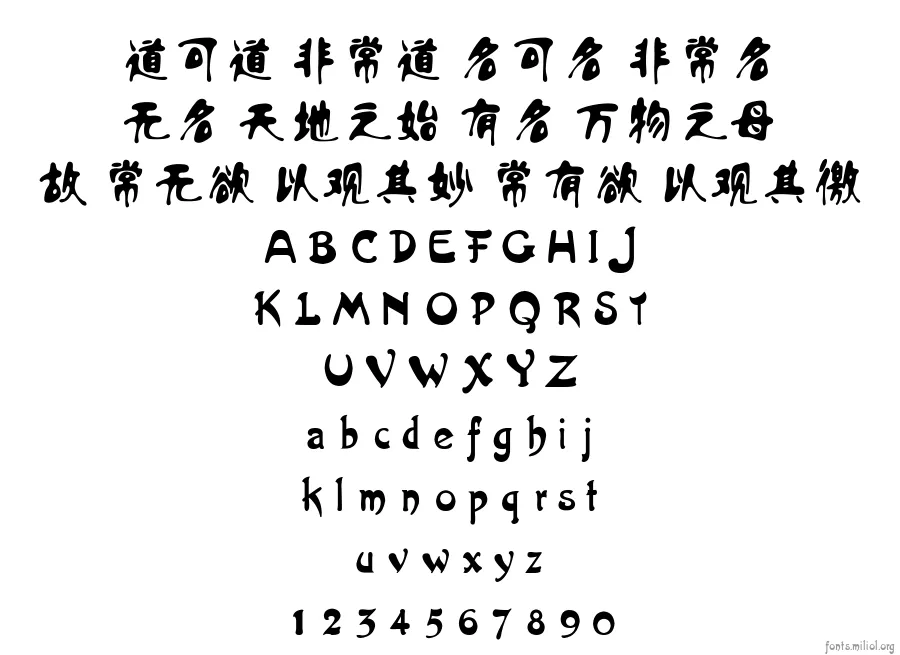
**方正流行体简体FZLiuXingTi-M26S:现代设计中的灵动之选**
方正流行体简体FZLiuXingTi-M26S是一款兼具时尚感与实用性的中文字体,其设计风格轻盈流畅,笔画间透露出鲜明的现代气息。字体结构简洁而不失个性,略微倾斜的笔触赋予文字动态美感,适合用于潮流品牌宣传、社交媒体设计、广告标语等需要突出年轻化与活力的场景。
这款字体在细节处理上尤为出色,横竖笔画的粗细对比适度,转折处圆润自然,既保证了易读性,又避免了过于呆板的传统字形。无论是标题大字还是短句排版,FZLiuXingTi-M26S都能为视觉呈现增添一抹灵动。此外,其简体字符集覆盖常用汉字,兼容多种设计软件,可无缝融入海报、短视频、电商页面等多媒体载体。
作为方正字库中的经典流行体,FZLiuXingTi-M26S以独特的风格平衡了创意与功能性,成为设计师应对快节奏视觉需求的优质选择。
FZLiuXingTi-M26S 字体映射图